بهترین فونتهای فارسی فانتزی کدام فونتها هستند؟
در دنیای طراحی گرافیک، فونت تنها یک ابزار برای نمایش متن نیست؛ بلکه روح طرح شماست. برای شما که بهعنوان گرافیست، ادیتور یا طراح فعالیت میکنید، انتخاب بهترین فونتهای فارسی فانتزی میتواند تفاوت بین یک کار معمولی و یک اثر هنری خیرهکننده باشد. در این مطلب از سایت دیاکوگرافیک قصد داریم تا ۵ تا از بهترین فونتهای فارسی فانتزی را به شما معرفی کنیم و با آنها آشنا بشویم تا بتوانید طرحهای قویتر را تولید کنید. پس با ما همراه باشید.
چرا استفاده از بهترین فونتهای فارسی فانتزی، سلاح مخفی طراحان حرفهای است؟
آیا تابهحال برایتان پیشآمده که طراحیتان کامل باشد، اما همچنان حس کنید چیزی کماست؟ مشکل اغلب در انتخاب فونت است. فونتهای فانتزی فارسی با شکستن کلیشهها،انرژی، هیجان و خالقیت را به طرحهای شما تزریق میکنند. این فونتها بهویژه در پوسترهای تبلیغاتی، کاورهای اینستاگرام و تایپوگرافیهای مدرن، نقش کلیدی در جذب مخاطب دارند.
چالش انتخاب فونت در پروژههای فارسی
بزرگترین چالش طراحان ایرانی، محدودیت در دسترسی به فونتهای استاندارد، خوانا و در عین حال جذاب است. استفاده از فونتهای تکراری باعث میشود طرح شما در میان انبوه محتوا گم شود. ما در این مقاله به شما کمک میکنیم تا با انتخاب هوشمندانه، هویت بصری منحصربهفردی بسازید.
چگونه بهترین فونتهای فارسی فانتزی را انتخاب کنیم؟
انتخاب فونت یک فرآیند حسی نیست، بلکه یک مهارت فنی است. برای انتخاب فونت مناسباین نکات را دنبال کنید:
- تحلیل مخاطب هدف: آیا طرح شما برای کودکان است یا یک برند لوکس؟
- بررسی خوانایی: فونتهای فانتزی نباید خوانایی را قربانی زیبایی کنند.
- توازن در ترکیببندی: فونت فانتزی باید با سایر عناصر طرح (تصاویر، رنگها) در تعادل
- باشد.
معرفی 5 تا از بهترین فونتهای فارسی فانتزی
فونت فارسی سرعت Sorat Font
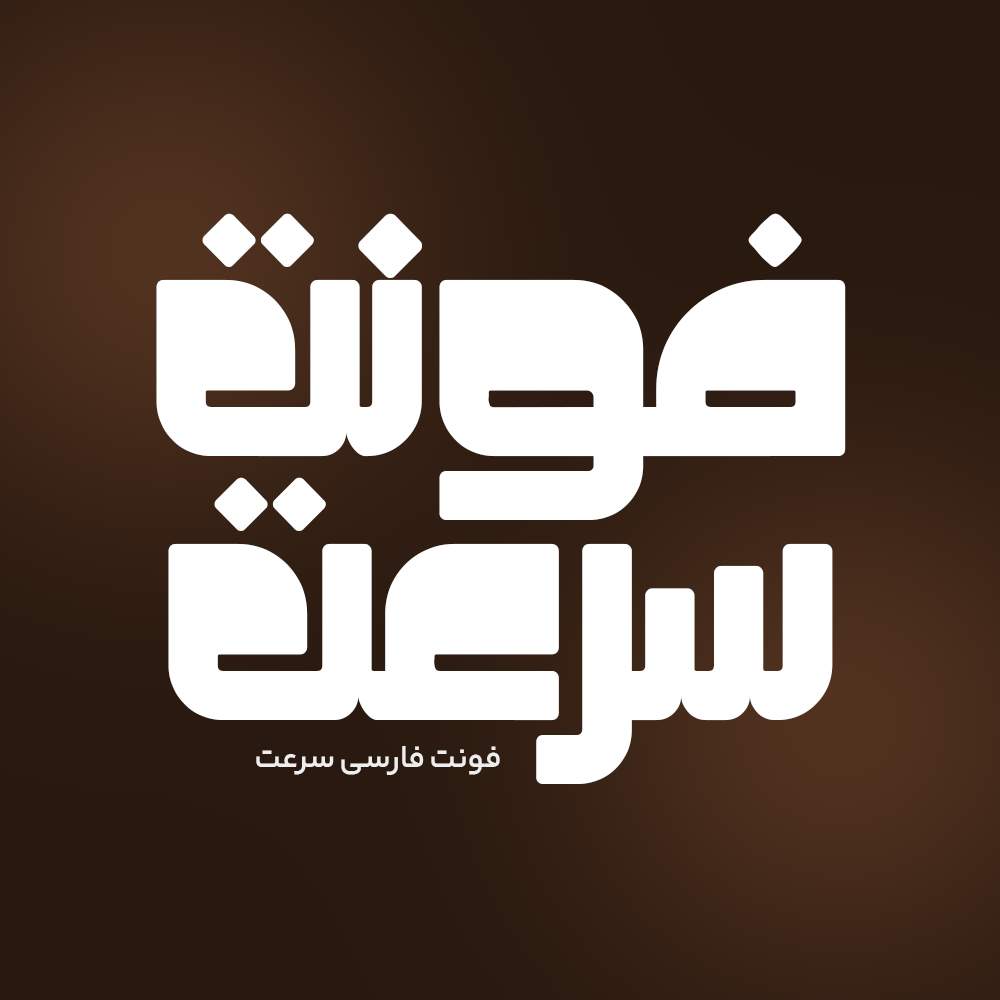
فونت فارسی لیالی Layaly Font
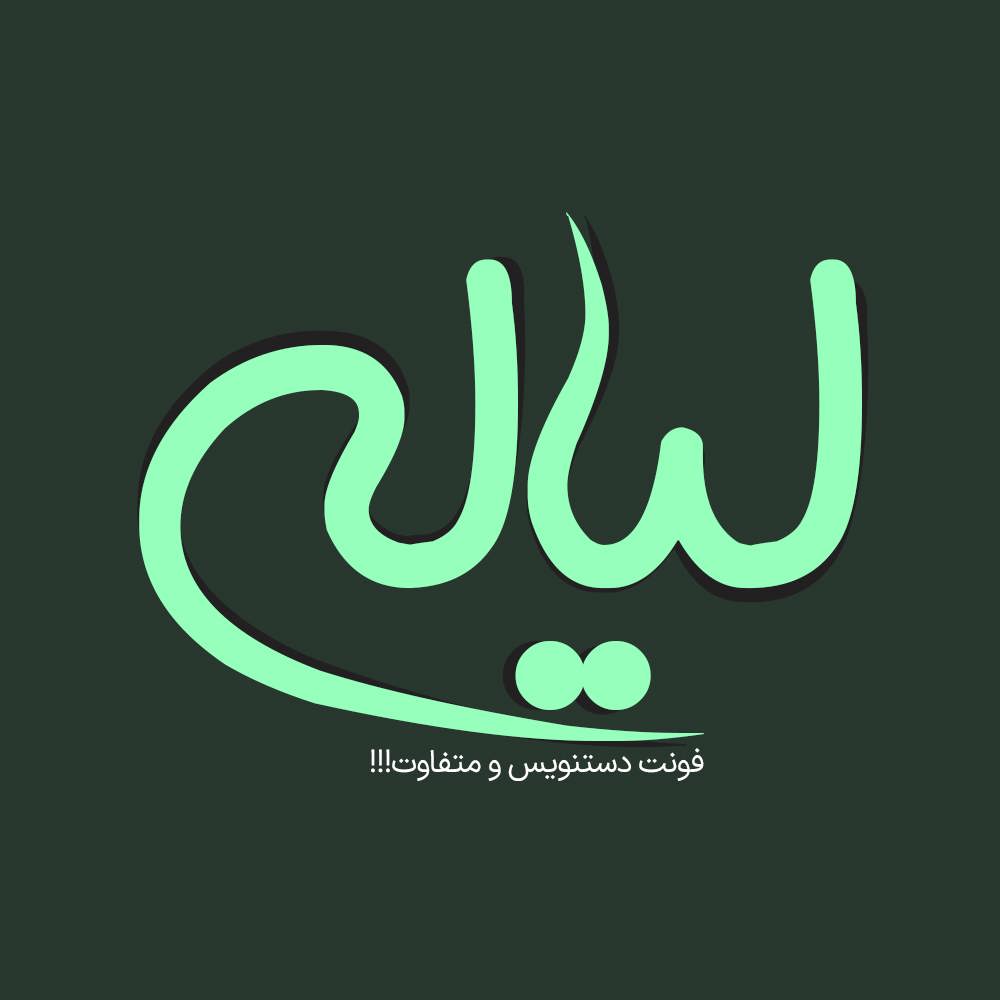
فونت فارسی فانتزی
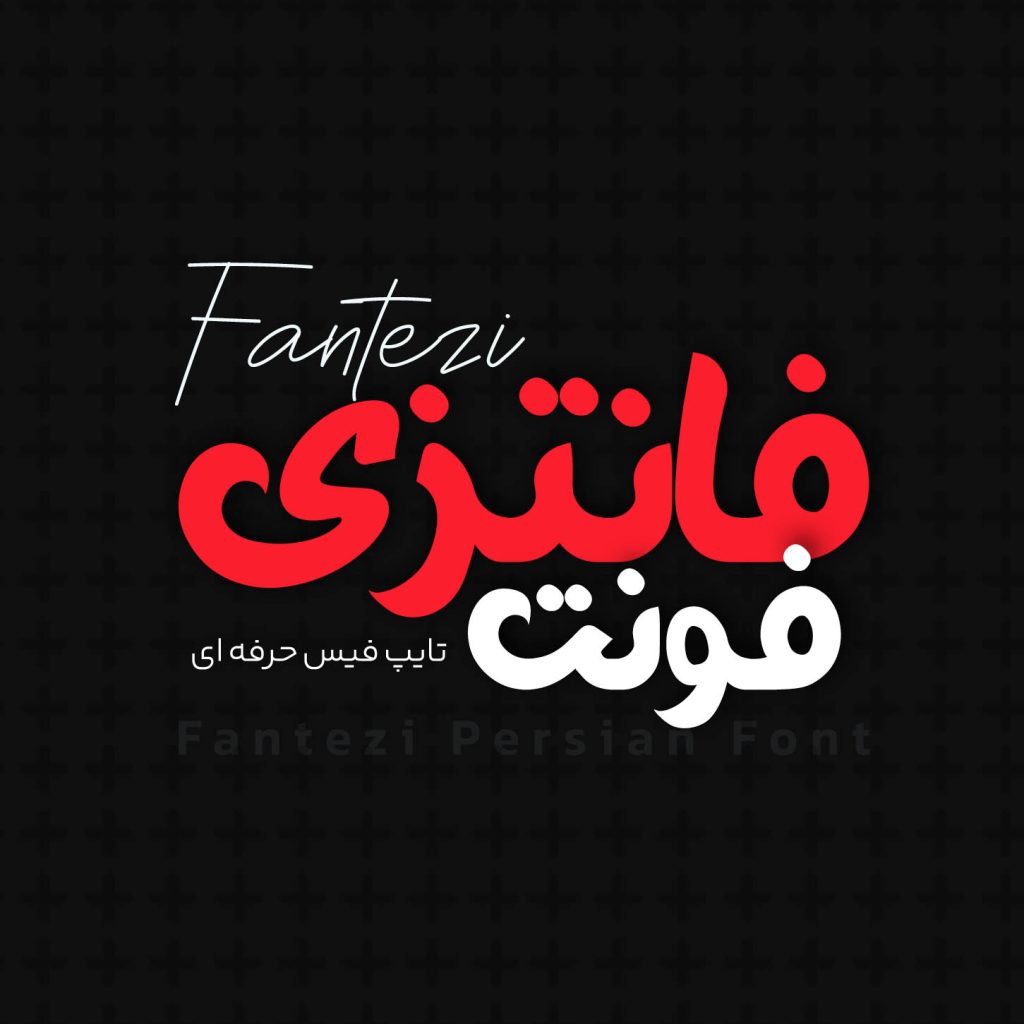
فونت فارسی تلگراف Telegraph Font
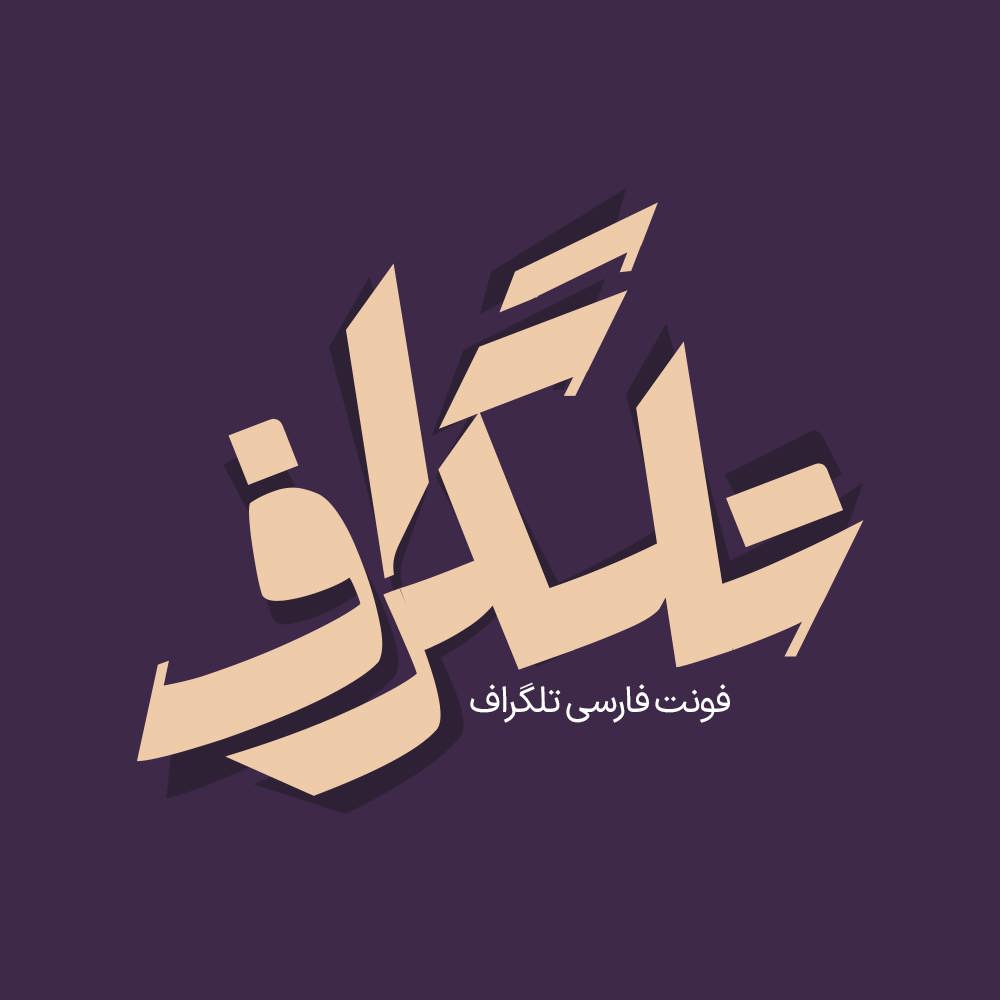
فونت فارسی گلاب Golab Font
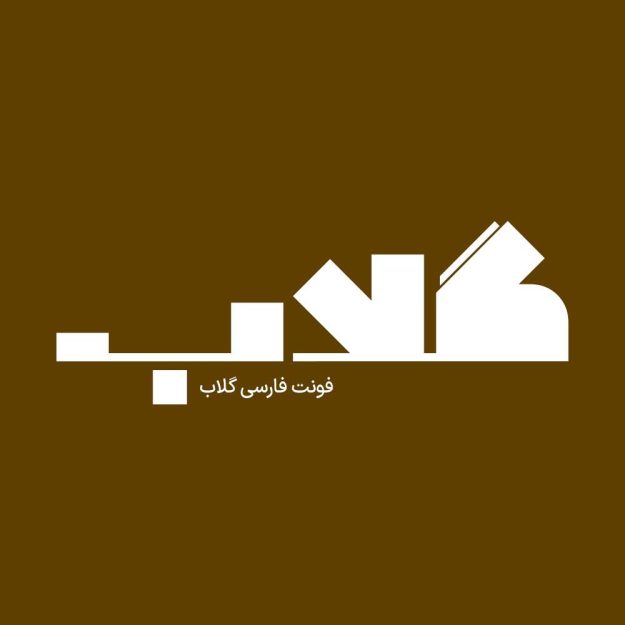
کلام آخر؛ مسیر موفقیت در طراحی
استفاده از بهترین فونتهای فارسی فانتزی تنها نیمی از راه است؛ نیمه دیگر، خالقیت شما در ترکیب این فونتها با اصول دیجیتال مارکتینگ و طراحی است. امیدواریم این راهنما شروعی باشد برای خلق آثاری که در ذهن مخاطب حک میشوند.